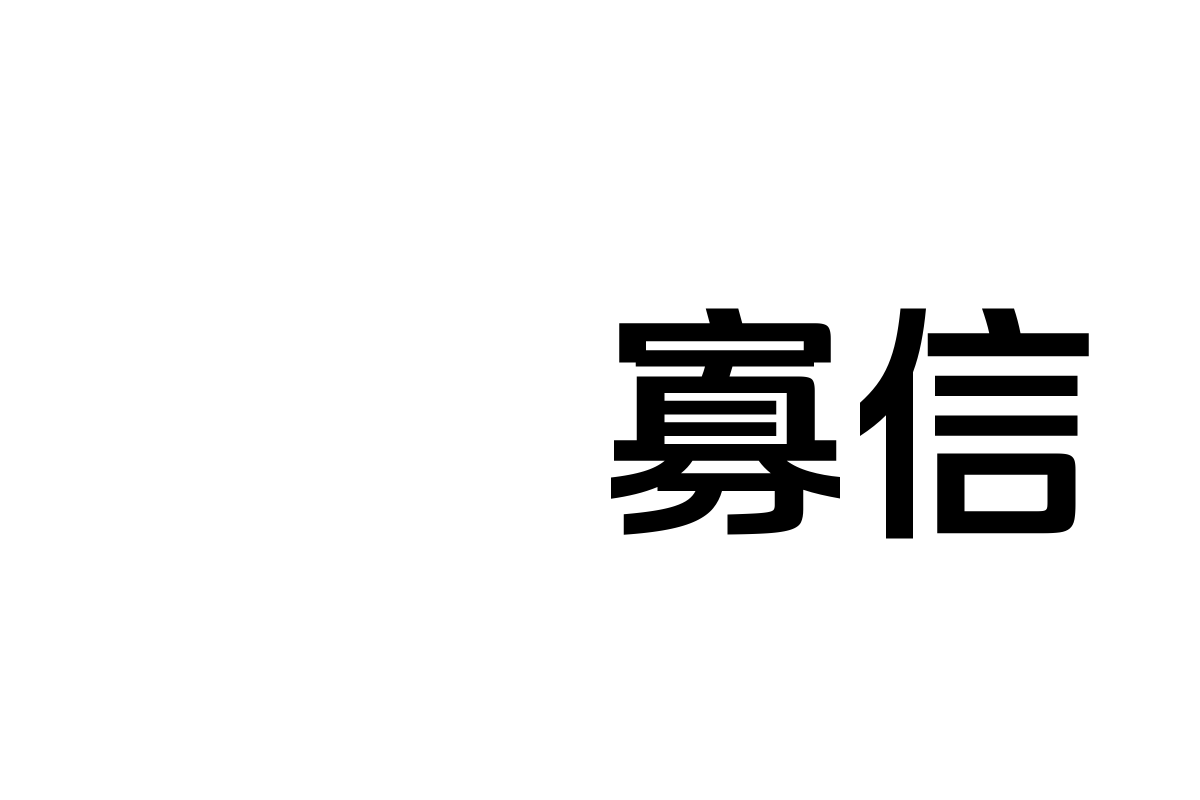
汉仪风尚黑B5-65是一款现代、时尚的中文字体,具有优雅流畅的线条和独特的风格。它适用于各种商业、广告、设计等领域,能够为作品增添一份独特魅力。这款字体的特点是字形结构简洁明了,笔画粗细适中,既有传统书法的韵味,又不失现代感。同时,它的字间距和行间距调整灵活,可以根据不同的需求进行个性化设置。总的来说,汉仪风尚黑B5-65是一款非常实用的中文字体,能够满足不同用户的需求。